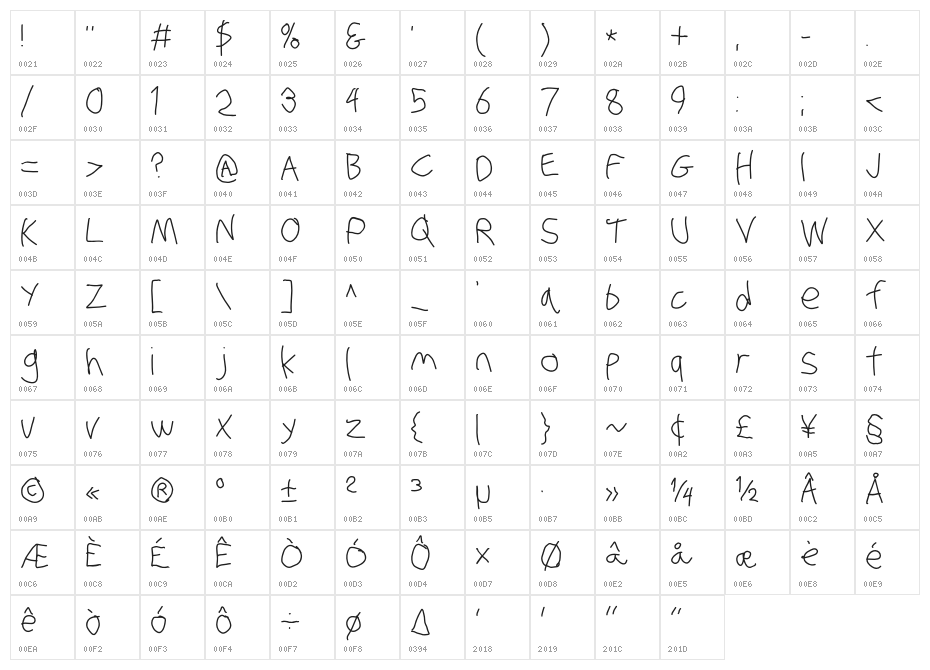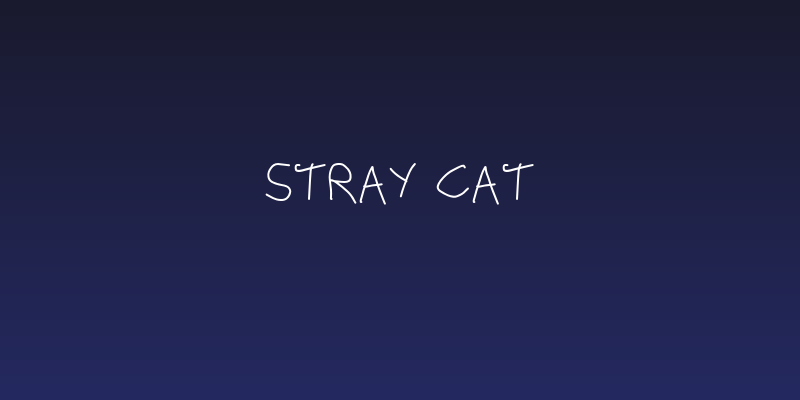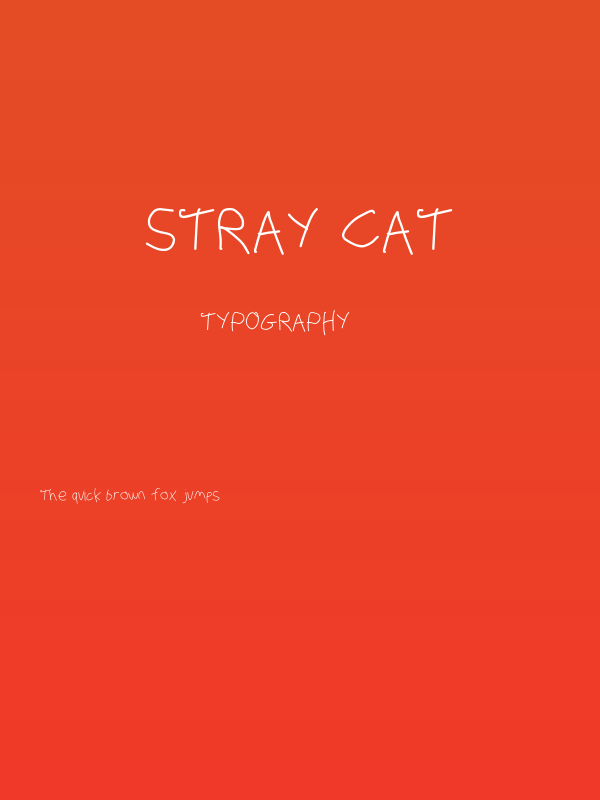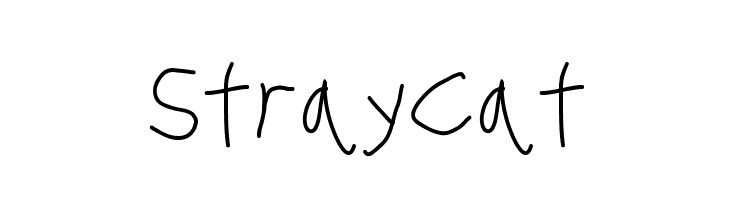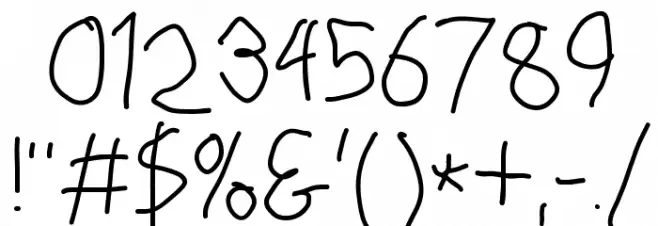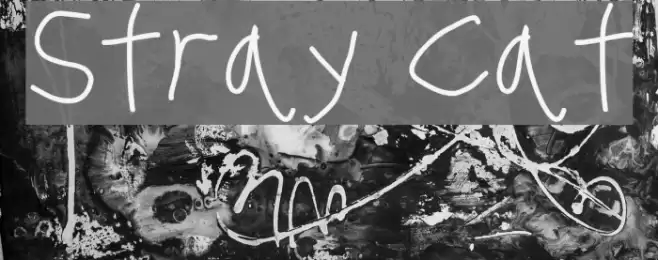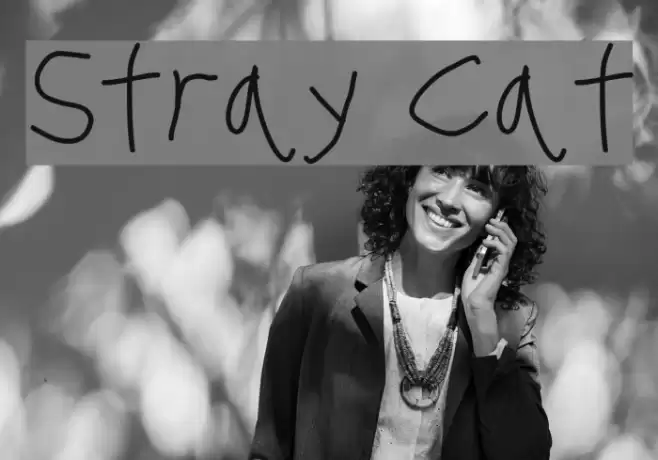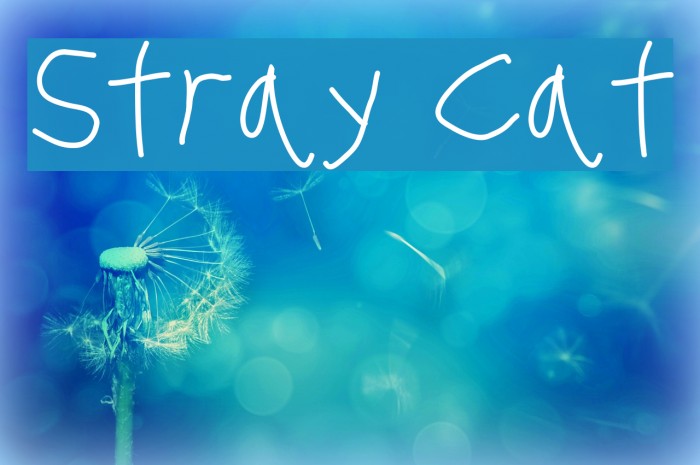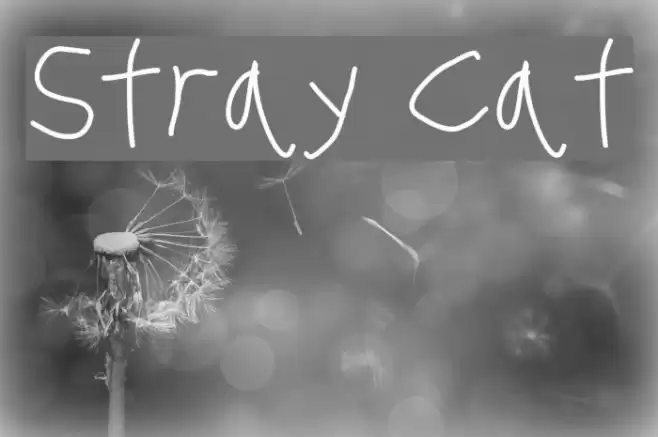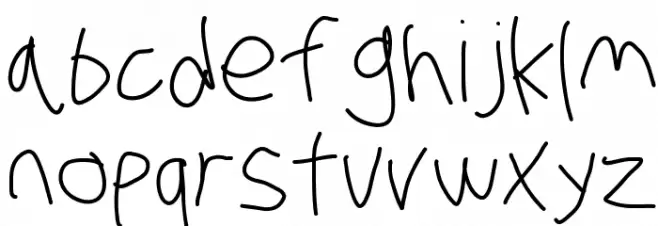
Stray Cat Font
| 名前 | Stray Cat |
| ウェイト | HlExtObl |
| 全体的なスタイル | Casual, Playful |
| 用途 | Headlines, Informal text, Personal projects |
| おすすめプロジェクト | Ideal for personal notes, greeting cards, children's books, casual branding, and social media graphics. |
| 作者 | Fonts by Claus Eggers Sørensen |